싸인을 만들 때 가장 고민되는 부분 중 하나가 바로 가독성을 우선할 것인지, 스타일을 강조할 것인지예요. 🤔
가독성이 좋은 싸인은 누구나 쉽게 읽을 수 있고, 공식적인 문서에도 적합해요. 반면, 스타일리시한 싸인은 예술적이고 개성이 넘치지만, 때때로 알아보기 어려울 수도 있죠. 그렇다면 어떤 싸인이 더 좋은 선택일까요? 🖋️
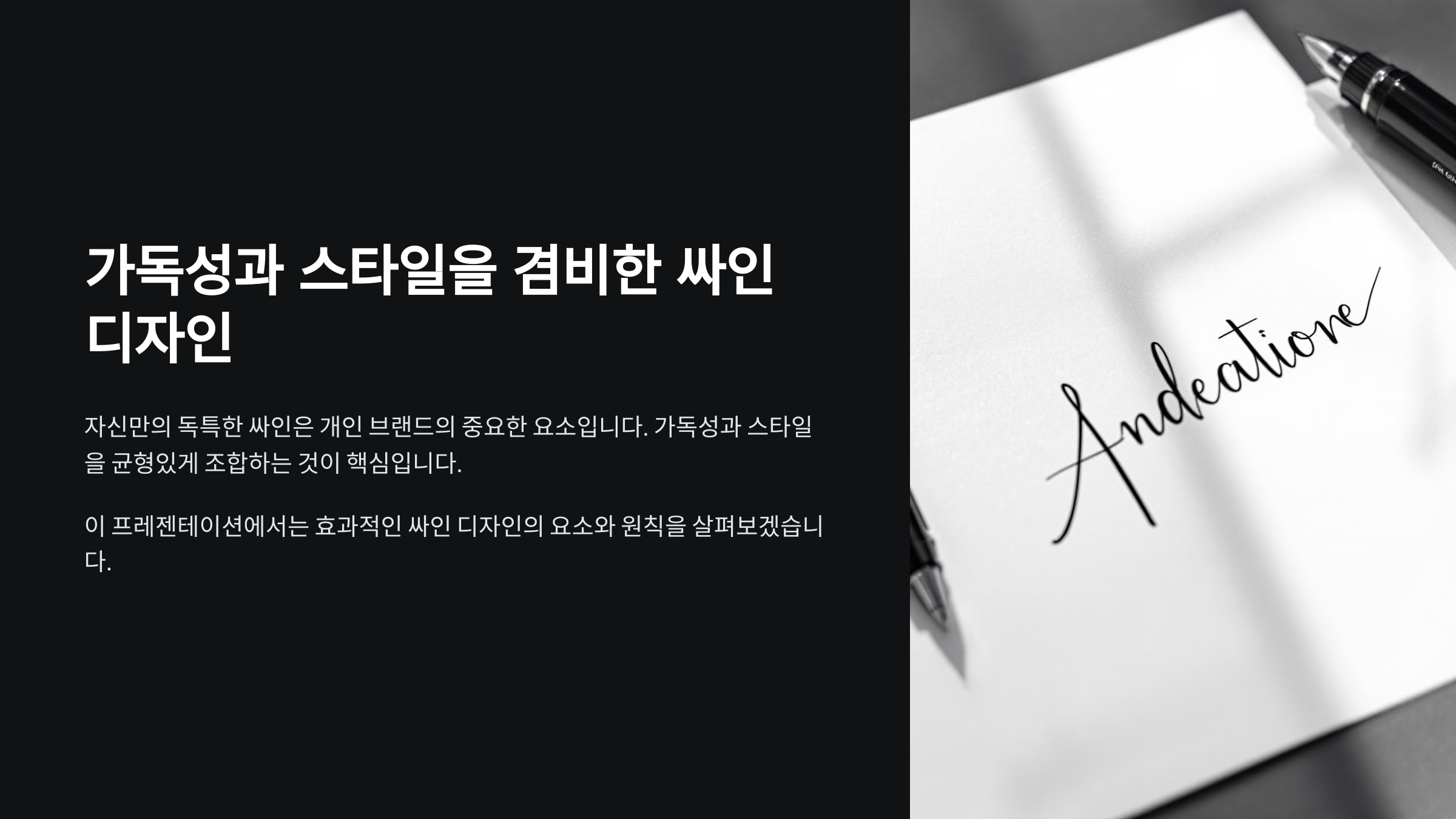
오늘은 가독성 좋은 싸인과 스타일리시한 싸인의 차이를 비교하고, 어떤 싸인이 어떤 상황에서 더 적합한지 분석해 볼게요! 🚀
가독성 좋은 싸인의 특징 🔍
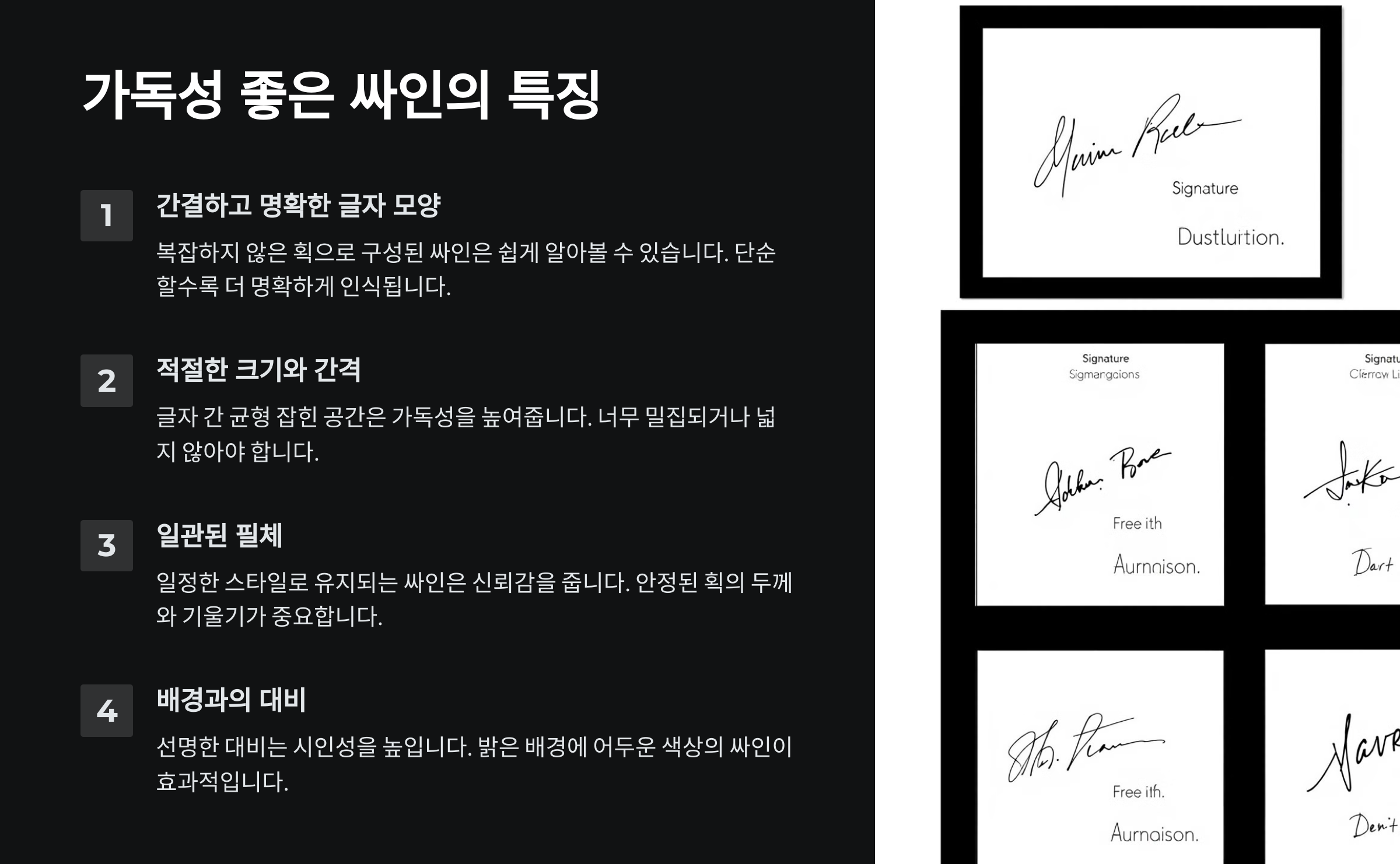
가독성이 좋은 싸인은 누가 봐도 쉽게 읽을 수 있는 서명이에요. 계약서, 신분증, 공문서 등에 사용할 때는 싸인의 가독성이 특히 중요해요. ✍️예를 들어, 빌 게이츠나 워런 버핏 같은 기업가들은 깔끔하고 읽기 쉬운 서명을 사용해요. 이는 공식적인 서류에서 신뢰감을 줄 뿐만 아니라, 빠르게 확인하고 검토하기에도 용이하죠. 📜
📌 가독성 좋은 싸인의 핵심 요소 ✅
특징 설명 대표 인물 명확한 글자 글자가 흐릿하지 않고, 또렷하게 보임 빌 게이츠 적절한 크기 너무 크거나 작지 않고, 적당한 크기 유지 워런 버핏 일관된 필체 서명할 때마다 비슷한 형태를 유지 버락 오바마 불필요한 장식 최소화 곡선이나 불필요한 요소 없이 깔끔한 스타일 팀 쿡 이처럼 가독성이 좋은 싸인은 실용적이고 공식적인 서류에 적합해요. 그렇다면, 반대로 스타일리시한 싸인은 어떤 특징을 가질까요? 🎨
스타일리시한 싸인의 특징 🎨
스타일리시한 싸인은 단순히 이름을 적는 것이 아니라, 예술적인 감각과 개성을 표현하는 서명이에요. 연예인, 예술가, 디자이너, 브랜드 CEO 등 창의적인 직업을 가진 사람들이 주로 스타일리시한 싸인을 사용하죠. ✍️✨
예를 들어, 살바도르 달리는 싸인에 독특한 필기체와 곡선을 강조했고, 일론 머스크는 빠르게 흘려 쓴 듯한 다이나믹한 싸인을 사용해요. 스타일리시한 싸인은 개성 있고 멋지지만, 가독성이 떨어질 수도 있다는 점을 고려해야 해요! 🎭
📌 스타일리시한 싸인의 핵심 요소 💎
특징 설명 대표 인물 예술적 필기체 곡선을 강조하고, 글자 모양을 변형하여 개성을 부각 살바도르 달리 다이나믹한 흐름 빠르게 휘갈겨 쓴 듯한 느낌으로 강한 인상을 줌 일론 머스크 독특한 심볼 추가 별, 하트, 밑줄 등 개성을 나타내는 심볼 활용 마이클 잭슨 디자인 요소 강조 싸인을 브랜드 로고처럼 만들거나, 시각적 요소 추가 샤넬 창립자 스타일리시한 싸인은 개성과 브랜드 이미지를 강화하는 데 좋지만, 공식적인 문서에서는 가독성 문제가 생길 수도 있어요. 그럼 가독성과 스타일 중 어떤 싸인이 더 좋을까요? 🤔
가독성 vs 스타일, 어떤 싸인이 더 좋을까? ⚖️
가독성이 좋은 싸인과 스타일리시한 싸인 중 어떤 싸인이 더 좋을까요? 사실 정답은 없어요. 중요한 것은 싸인의 목적과 사용 환경에 맞게 선택하는 것이에요! ✅
예를 들어, 계약서, 신분증, 은행 서류처럼 공식적인 문서에서는 가독성이 중요해요. 반면, 연예인, 아티스트, 스포츠 스타처럼 대중적인 인지도를 가진 사람들은 스타일을 강조한 싸인을 사용해요. 🎨
📌 가독성 싸인 vs 스타일리시한 싸인 비교표 📊
비교 항목 가독성 좋은 싸인 스타일리시한 싸인 읽기 쉬움 높음 (누구나 쉽게 인식 가능) 낮음 (디자인 요소가 많아 읽기 어려울 수도 있음) 공식 문서 적합성 매우 적합 (계약서, 은행 서류 등에 필수) 부적합 (공식 문서에서 사용 어려움) 개성 표현 낮음 (단순하고 깔끔한 스타일) 높음 (예술적인 감각을 표현 가능) 빠른 작성 보통 (일관된 형태 유지 가능) 빠름 (휘갈겨 쓰는 스타일 가능) 대표 인물 빌 게이츠, 워런 버핏, 버락 오바마 살바도르 달리, 일론 머스크, 마이클 잭슨 결국, 싸인의 스타일은 사용 목적과 상황에 따라 다르게 선택하는 것이 중요해요! 그럼 실제 어떤 경우에 가독성이 중요한지, 어떤 경우에 스타일이 중요한지 살펴볼까요? 🧐
사용 목적에 따라 적합한 싸인 선택하기 🎯
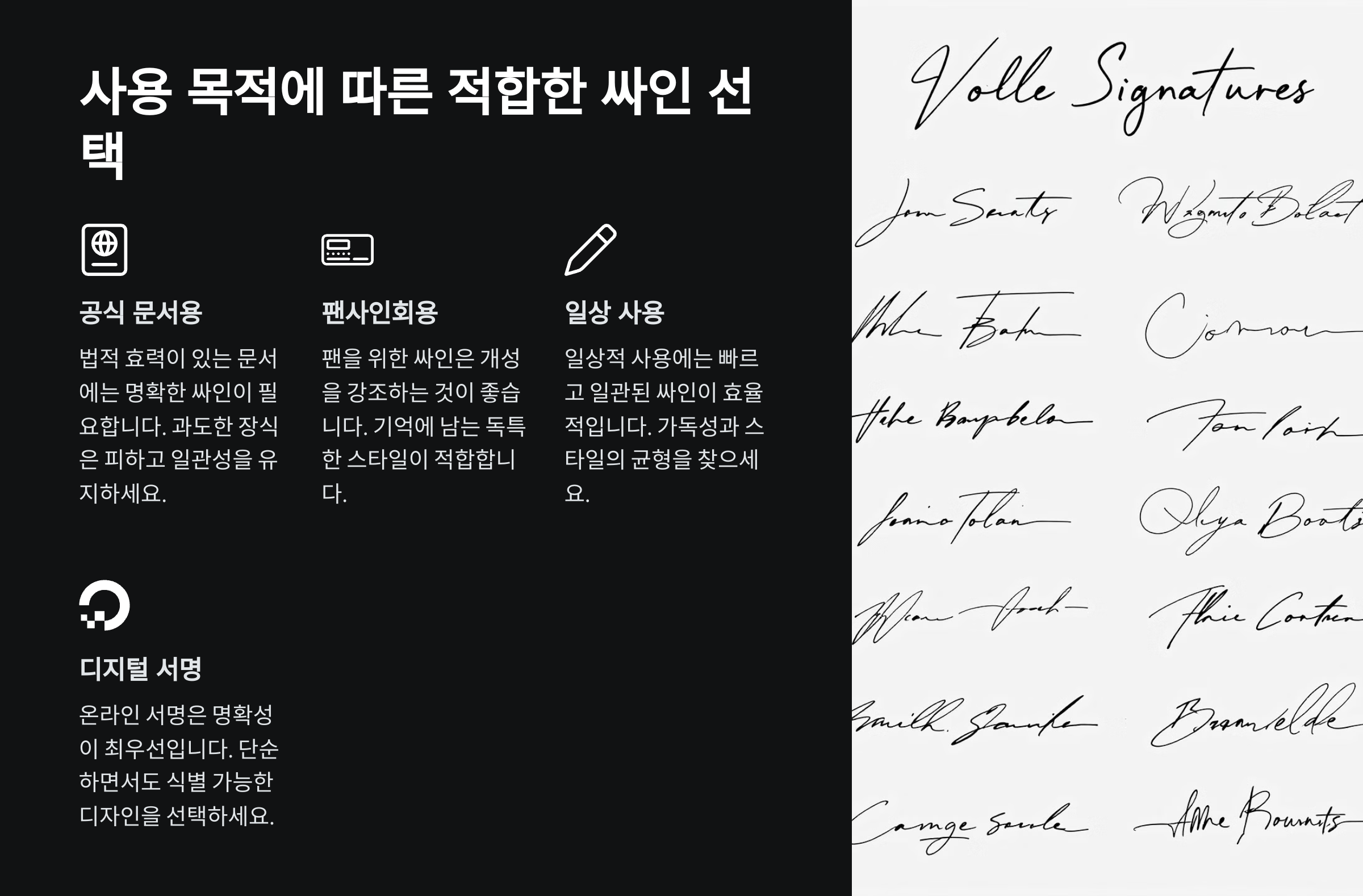
싸인을 사용할 목적에 따라 가독성이 중요한 경우와 스타일이 중요한 경우가 달라요. 따라서 싸인을 만들 때는 어디에 사용할 것인지 먼저 고려하는 것이 중요해요! 🖊️
예를 들어, 계약서와 공문서에 사용할 싸인은 명확해야 하지만, 팬 사인회에서 사용할 싸인은 개성이 돋보여야겠죠? 🤔
📌 싸인 사용 목적별 추천 스타일 ⚡
사용 목적 추천 스타일 예시 인물 계약서, 공문서 가독성이 좋은 싸인 (깔끔하고 명확한 필체) 빌 게이츠, 워런 버핏 브랜드 로고 스타일리시한 싸인 (디자인 요소 추가) 샤넬 창립자 팬 사인회 스타일리시한 싸인 (심볼, 장식 추가) 마이클 잭슨, BTS 명함, 개인 브랜딩 균형 잡힌 싸인 (가독성과 스타일 조화) 일론 머스크 이처럼 싸인의 사용 목적에 따라 적절한 스타일을 선택하면, 실용성과 개성을 동시에 살릴 수 있어요. 그럼 유명인들의 싸인 스타일을 분석하면서 어떤 요소들이 있는지 살펴볼까요? 🌟
유명인의 싸인 스타일 분석 🌟
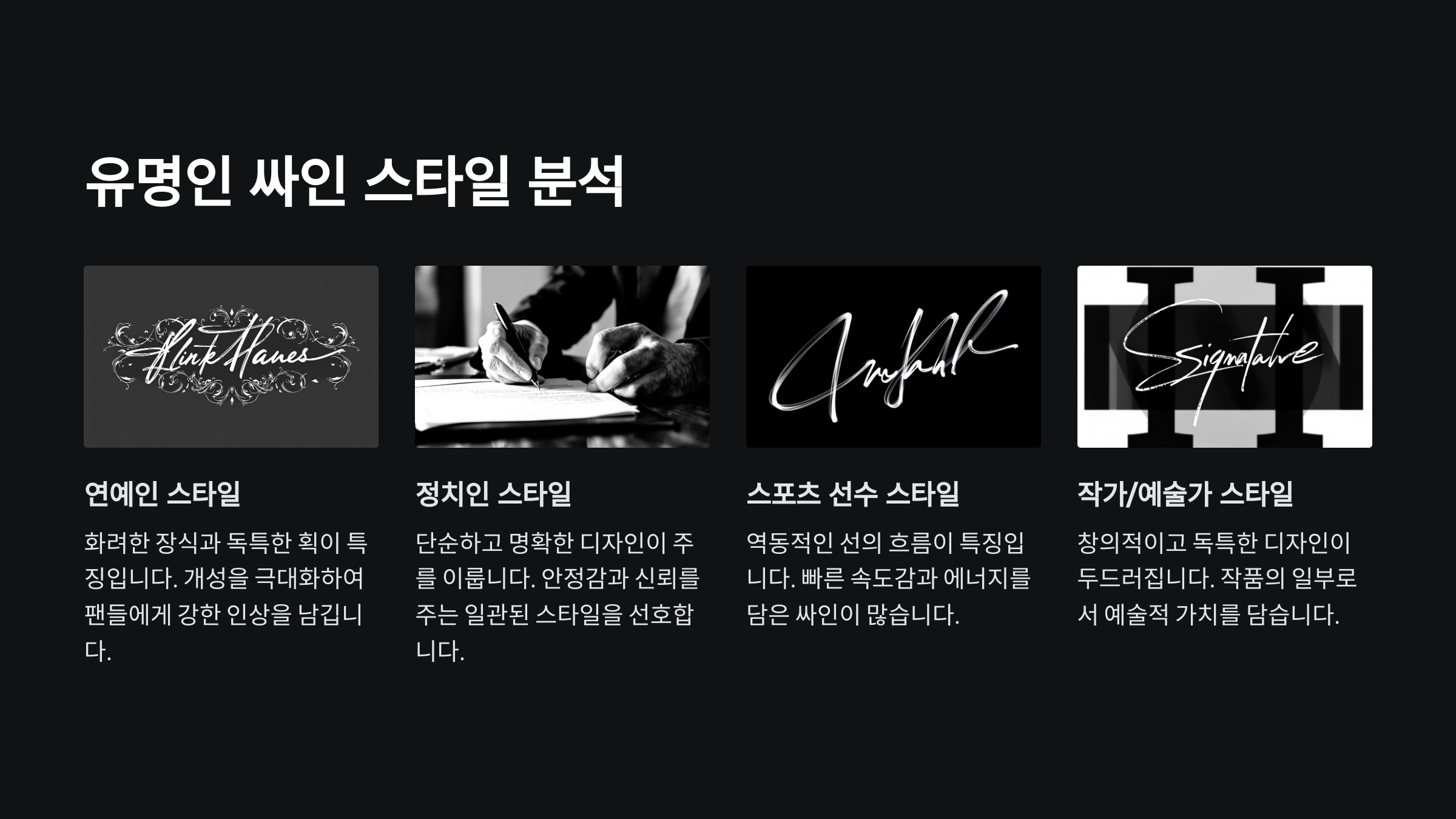
유명인들의 싸인은 단순한 서명이 아니라, 그들의 브랜드와 개성을 표현하는 중요한 요소예요. 스타일이 독특한 싸인들은 팬들에게 강한 인상을 남기고, 공식 문서에서도 한눈에 알아볼 수 있는 특징이 있죠! ✍️
오늘은 세계적으로 유명한 인물들의 싸인을 분석하면서, 어떤 스타일이 사용되는지 살펴볼게요! 🎭
📌 유명인의 싸인 스타일 비교 🔍
인물 싸인 스타일 특징 🖋️ 빌 게이츠 가독성이 뛰어난 싸인 깔끔하고 정갈한 필기체, 읽기 쉬움 🎨 살바도르 달리 예술적인 싸인 곡선과 장식 요소 활용, 개성 강조 🚀 일론 머스크 빠르고 간결한 싸인 휘갈겨 쓴 듯한 스타일, 속도감 강조 🎤 마이클 잭슨 스타일리시한 싸인 별(★) 장식 포함, 독창적 디자인 🏆 크리스티아누 호날두 강렬한 필기체 싸인 굵고 선명한 필체, 강한 인상 남김 이처럼 싸인은 단순한 서명을 넘어서, 개성과 브랜드를 표현하는 중요한 도구가 될 수 있어요. 그럼 가독성과 스타일을 균형 있게 조합하는 꿀팁도 살펴볼까요? 💡
균형 잡힌 싸인을 만드는 꿀팁 💡
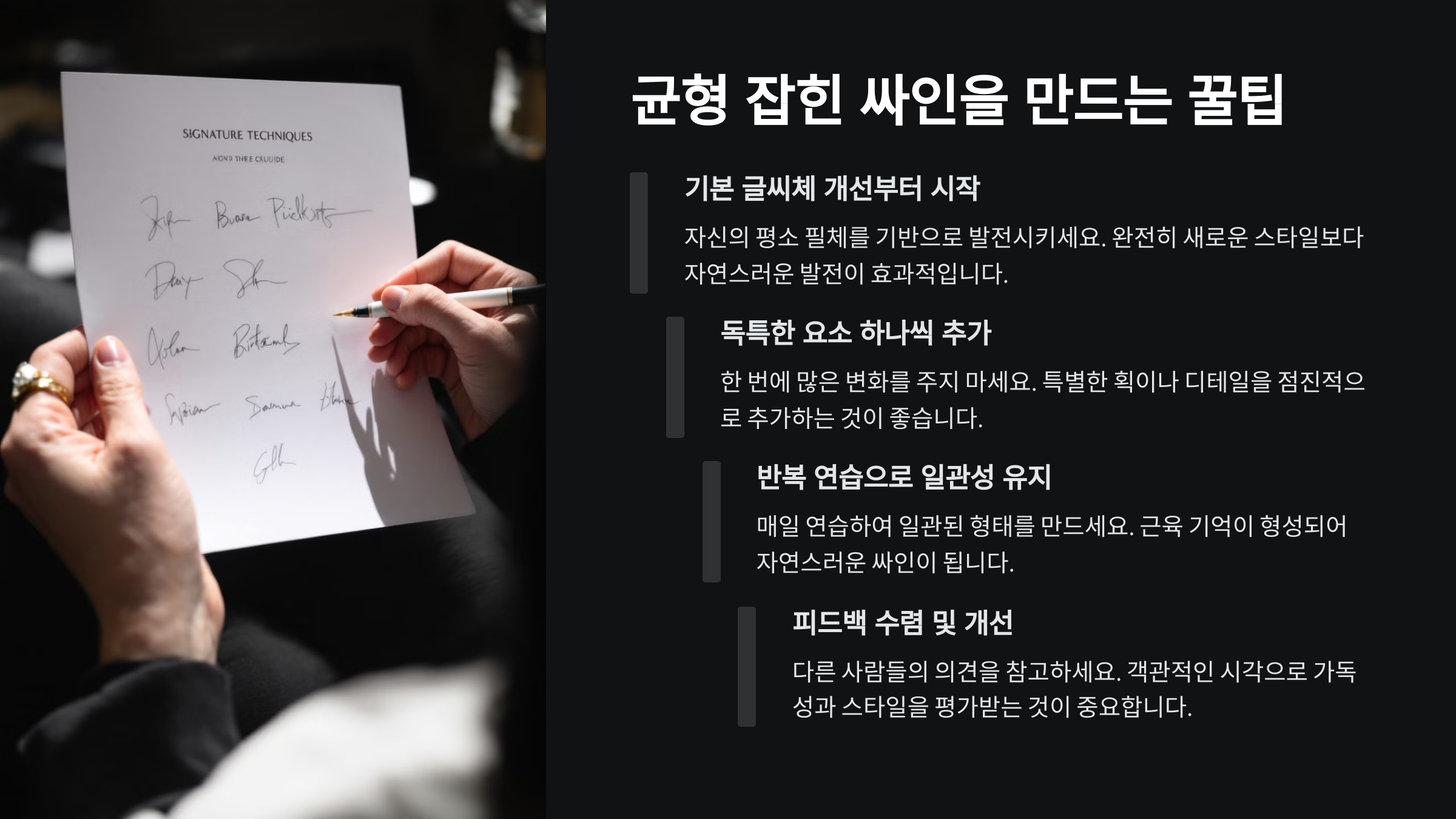
가독성이 좋은 싸인과 스타일리시한 싸인, 두 가지의 장점을 모두 살린 완벽한 싸인을 만들 수 있을까요? 답은 YES! 🎯 적절한 균형을 맞추면 읽기 쉬우면서도 멋진 싸인을 완성할 수 있어요.
예를 들어, 일론 머스크는 간결하면서도 독창적인 싸인을, 빌 게이츠는 읽기 쉽지만 개성이 담긴 싸인을 사용해요. 이처럼 가독성과 스타일을 적절히 조화하면, 공식 문서에서도 사용할 수 있고, 브랜드 이미지도 살릴 수 있는 싸인을 만들 수 있어요! ✅
📌 가독성과 스타일을 조화롭게 만드는 5가지 방법 🖊️
방법 설명 1. 기본 틀 유지 이름을 알아볼 수 있도록 기본 형태는 유지하기 2. 곡선과 직선 조합 글씨의 일부를 부드럽게 흘려 쓰면서, 직선도 활용 3. 불필요한 장식 줄이기 스타일을 살리되, 너무 복잡하지 않도록 조절 4. 서명 속도 연습 빠르게 서명해도 일관된 형태가 유지되도록 연습 5. 심볼 활용 (선택 사항) 스타일을 살리기 위해 별, 밑줄 등의 작은 포인트 추가 이제 자신만의 균형 잡힌 싸인을 만들 수 있는 방법을 알게 되었어요! 마지막으로, 사람들이 자주 묻는 싸인 관련 질문들을 FAQ로 정리해 볼게요. 📢
FAQ
Q1. 싸인을 가독성 있게 하면서도 개성을 살릴 방법이 있을까요?
A1. 네! 기본적인 글씨는 유지하면서, 곡선이나 작은 장식을 추가하면 개성을 살릴 수 있어요. ✍️
Q2. 너무 단순한 싸인은 식별이 어려울까요?
A2. 싸인이 너무 단순하면 위조가 쉬울 수 있어요. 적절한 개성을 추가하는 것이 좋아요. 🔍
Q3. 스타일리시한 싸인을 공식 문서에 사용해도 될까요?
A3. 공식 문서에서는 가독성이 중요한 경우가 많아요. 중요한 서류에는 깔끔한 싸인을 사용하는 것이 좋아요. 📜
Q4. 싸인을 연습하는 가장 좋은 방법은?
A4. 원하는 스타일을 정한 후, 여러 번 반복해서 연습하며 자연스럽게 쓰는 것이 중요해요. 🖋️
Q5. 싸인에 밑줄이나 기호를 넣으면 안 될까요?
A5. 밑줄이나 기호를 적절히 활용하면 개성이 강조될 수 있지만, 너무 과하면 가독성이 떨어질 수 있어요. 🚀
Q6. 싸인의 크기는 어느 정도가 적당한가요?
A6. 너무 크면 공간을 차지하고, 너무 작으면 눈에 띄지 않으니 적당한 크기로 조절하는 것이 중요해요. ✏️
Q7. 싸인을 바꿔도 괜찮을까요?
A7. 네, 하지만 공식 문서에 등록된 싸인과 다르면 문제가 될 수 있으니 주의하세요. ⚠️
Q8. 싸인을 만들 때 가장 중요한 요소는?
A8. 싸인의 사용 목적, 가독성, 개성을 고려하여 자신만의 스타일을 찾는 것이 중요해요! 💡